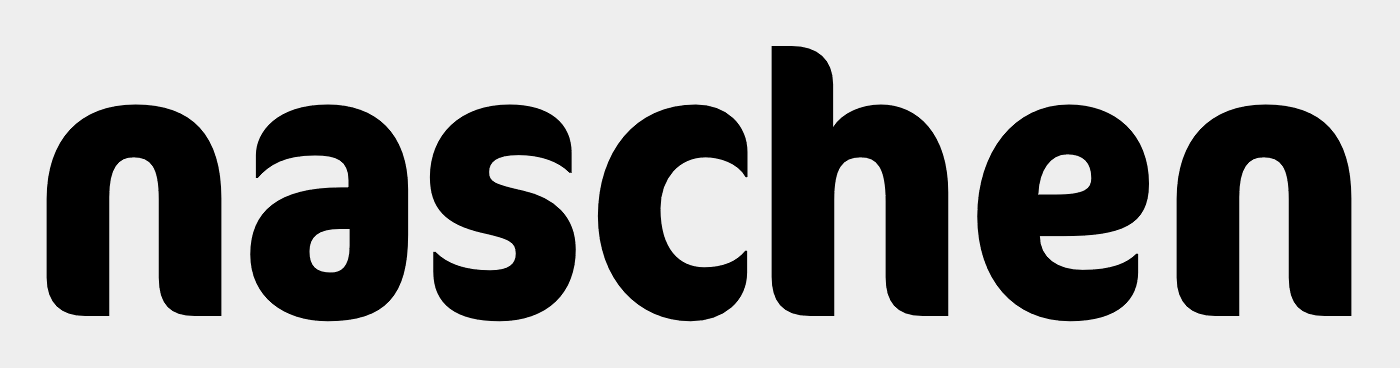
Rundliche Schrift mit weichen Enden, nur welche?
Leider sind die Bilder etwas unscharf, aber ich denke die wesentlichen Merkmale sind erkennbar.
Vielleicht kennt jemand eine Schrift die so ähnlich aussieht?
Ich habe schon "Kiro Extra Bold" gefunden, aber das h und das c ist doch noch ein bisschen anders.